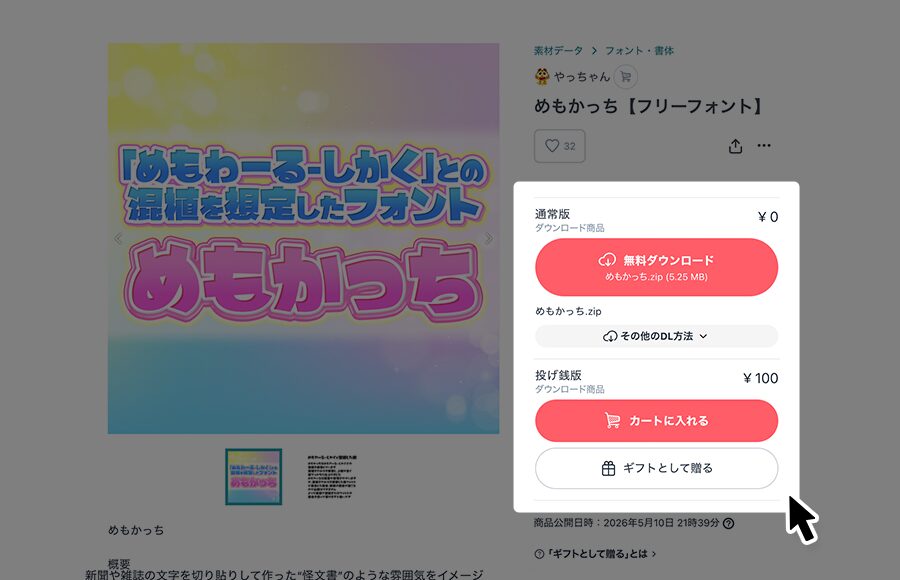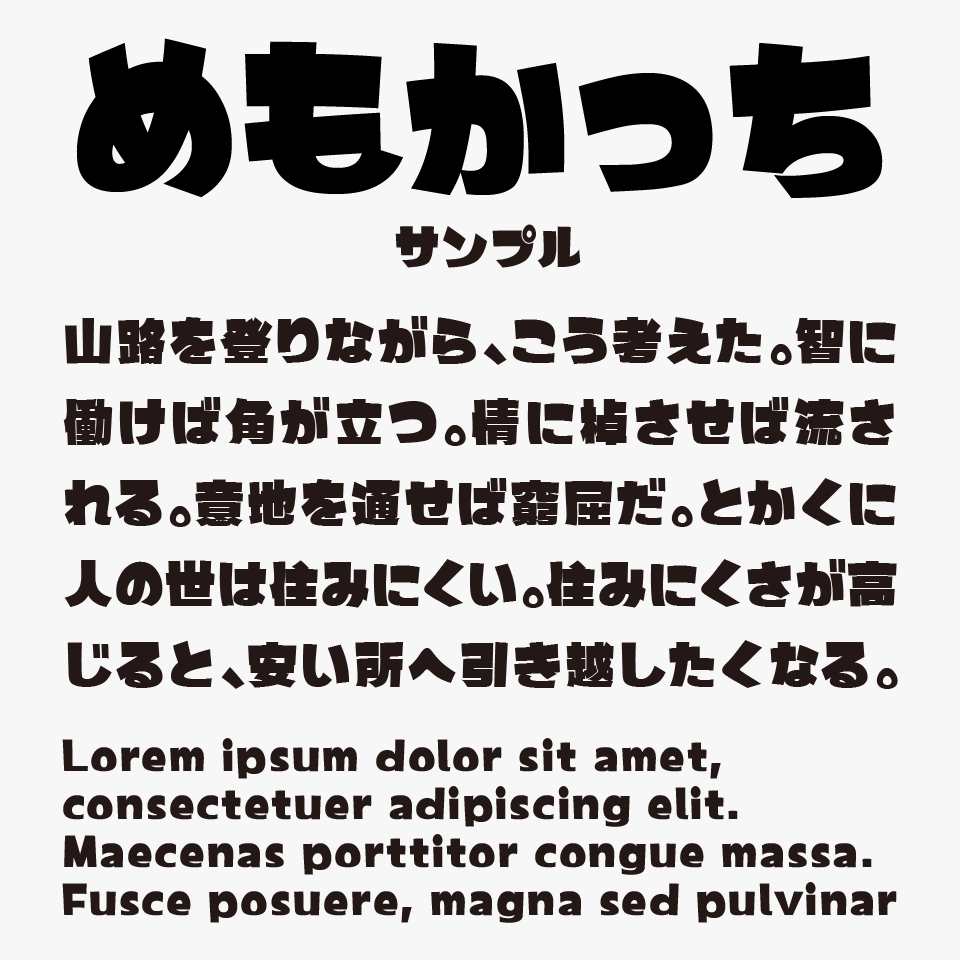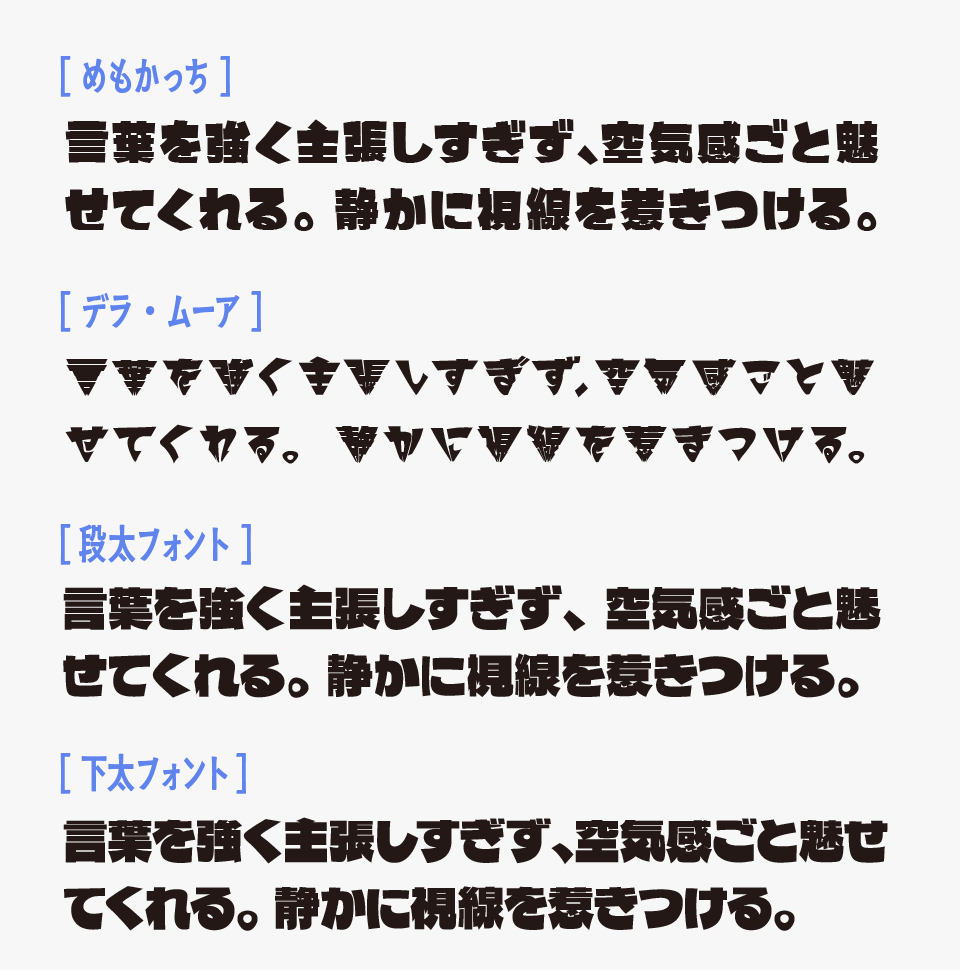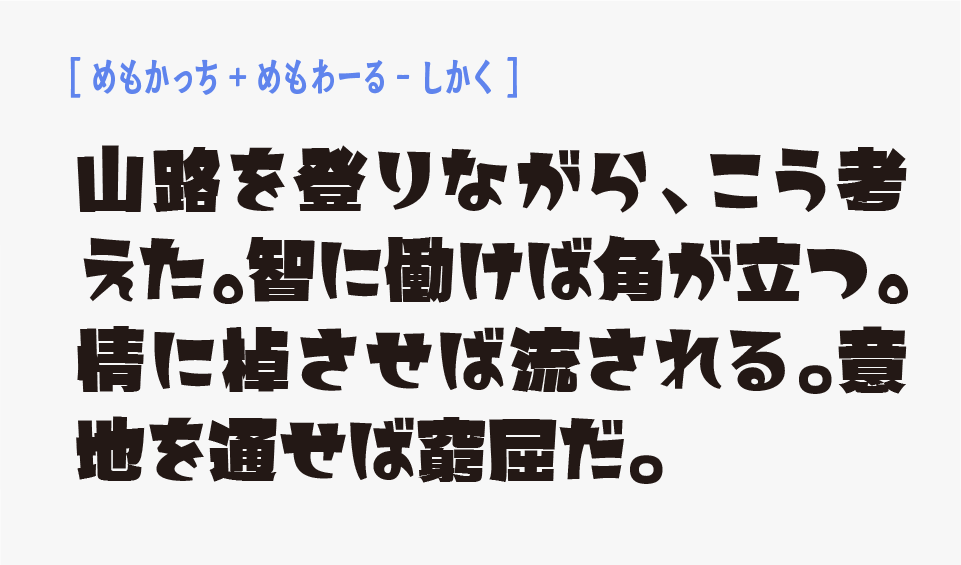
めもかっちフォントは、「源暎きわみゴ」フォントをベースに加工し、ぎゅっと下にすぼんだ太めの字形と少し傾いたバランスによって、可愛らしさを感じるデザイン系ゴシックフォントです。
シルエットが親しみやすく、太めながら圧迫感が少なく、どこかゆるさも残しているため、コミカルな場面にも使いやすいフォントです。
バラエティ系テロップやポップな見出し、動画サムネイルなどと相性が良く、にぎやかでテンポ感のあるデザインを作りたい時にぴったりなフォントです。
めもかっち
めもかっちフォントは、「めもわーる‐しかく」フォントと混植されることを前提に設計されているため、フォントを組み合わせたデザインとも非常に相性が良いフォントです。
「めもかっち」と「めもわーる‐しかく」フォントと混植事例
下にきゅっとすぼんだようなスタイルをもつフォントと比較すると、めもかっちフォントは、ポップでコミカルな印象を感じます。
比較フォントは「デラ・ムーア」「段太フォント」「下太フォント」と使用していますが、どのフォントもとてもステキななので、あわせてチェックしてみてください。
めもかっちフォントと、「デラ・ムーア」「段太フォント」「下太フォント」を比較